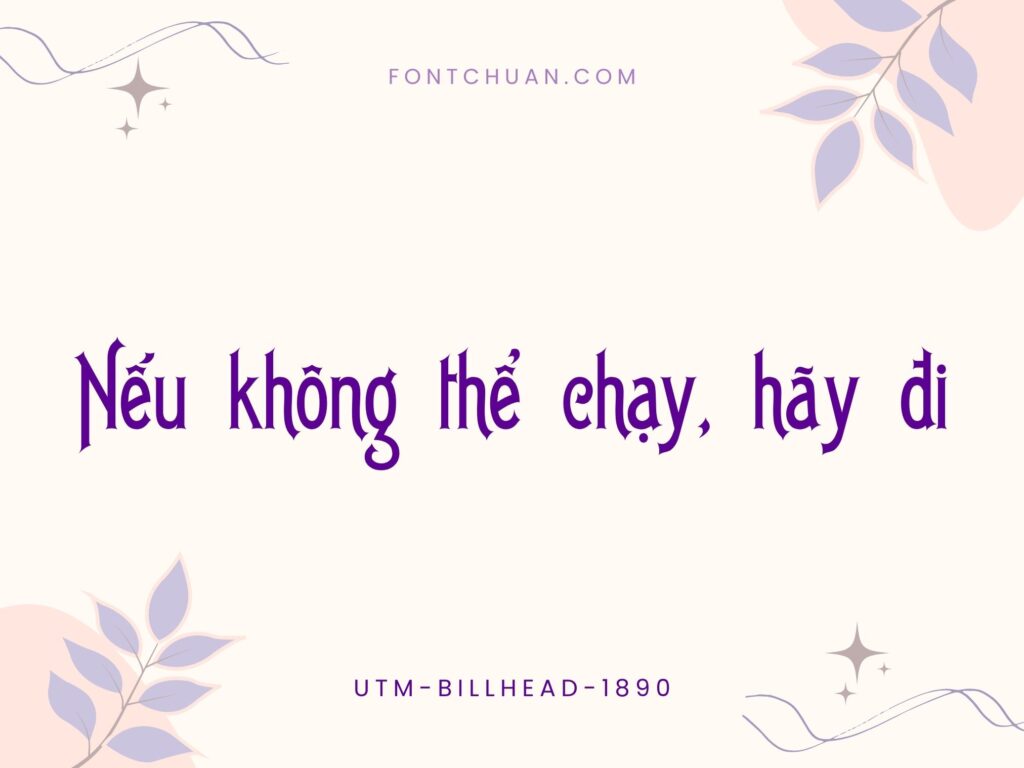
Font UTM Billhead 1890 Việt Hóa
UTM Billhead 1890 là phiên bản Việt hóa của font chữ LHF Billhead 1890, một kiểu chữ decorative/display mang phong cách Font Vintage, được thiết kế với các đường nét trang trí tinh xảo và phức tạp, gợi nhớ đến các biển hiệu và tiêu đề từ cuối thế kỷ 19. Font này nổi bật với các ký tự in hoa có sự hiện diện mạnh mẽ, chân chữ sắc nét và các đường cong độc đáo, tạo nên vẻ đẹp cổ điển và sang trọng. Phiên bản Việt hóa đã được thực hiện, hỗ trợ đầy đủ tiếng Việt cùng hơn 100 ngôn ngữ khác. Đây là một trong những font được cộng đồng thiết kế sưu tầm và chọn lọc nhằm đáp ứng nhu cầu đa dạng trong thiết kế.
UTM Billhead 1890 có cấu trúc chữ với các nét trang trí phức tạp và độ tương phản cao, tạo nên sự nổi bật và thu hút. Font này phù hợp cho các ứng dụng như thiết kế tiêu đề, logo, biển hiệu, áp phích và các ấn phẩm in ấn yêu cầu sự cổ điển và nghệ thuật. Các ngành nghề như quảng cáo, giáo dục, công nghệ và bất động sản có thể tận dụng UTM Billhead 1890 để tạo điểm nhấn độc đáo trong thiết kế.